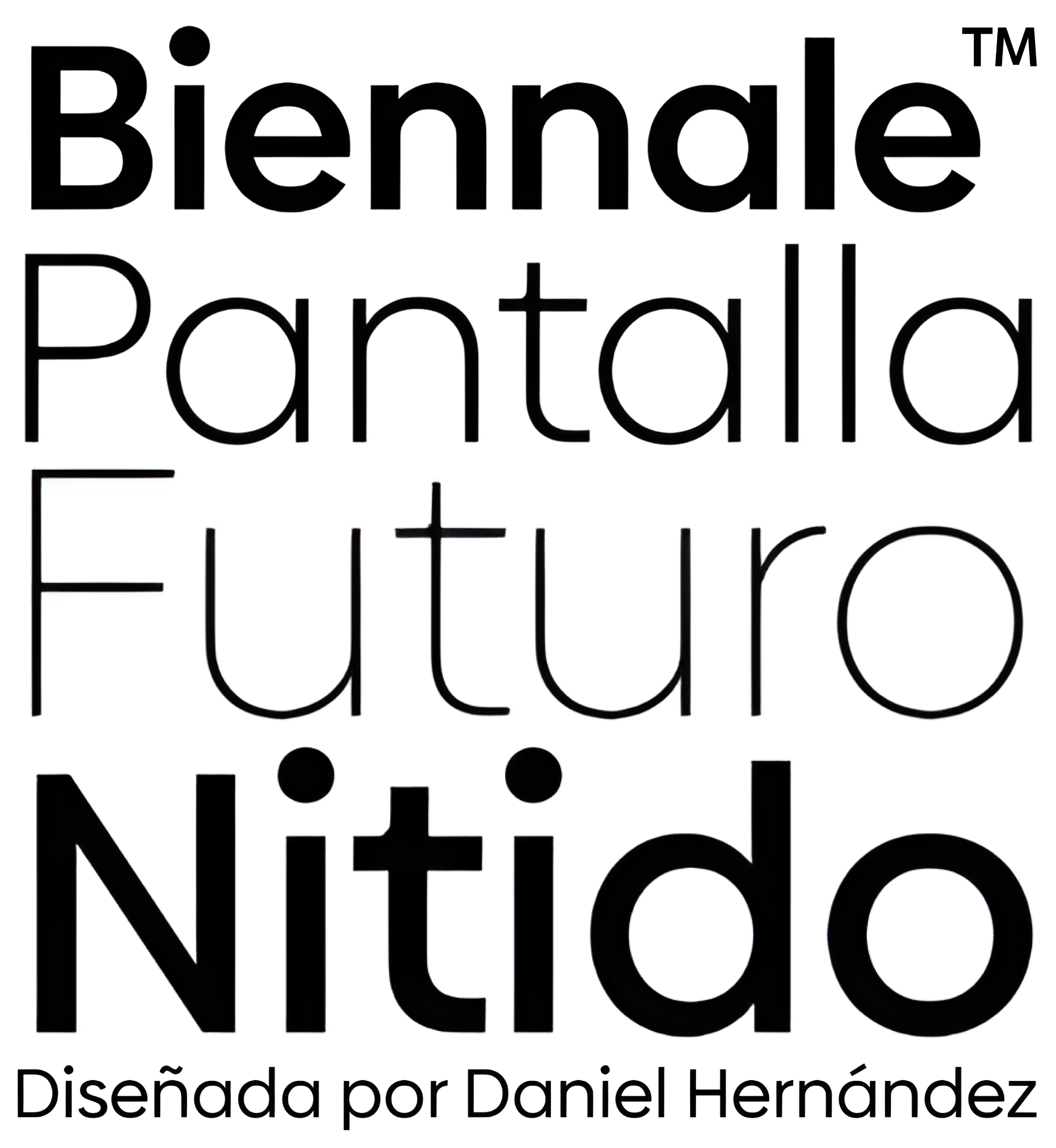
| Créditos | Daniel Hernández |
| Descripción | Biennale es una tipografía geométrica con un fuerte carácter y una gran altura x que la convierten en una opción excelente para una amplia gama de aplicaciones, como titulares o marcas. Aunque de estilo común, los detalles distintivos de Biennale y su color en la página permiten a los usuarios crear diseños realmente únicos. La fuente está disponible en 11 pesos, de Hair a Heavy, e incluye cursivas a juego. Como cabe esperar de Latinotype, este tipo de letra viene con un conjunto estándar de 417 caracteres compatibles con más de 200 lenguas de base latina. |
| Familia(s) | Biennale |